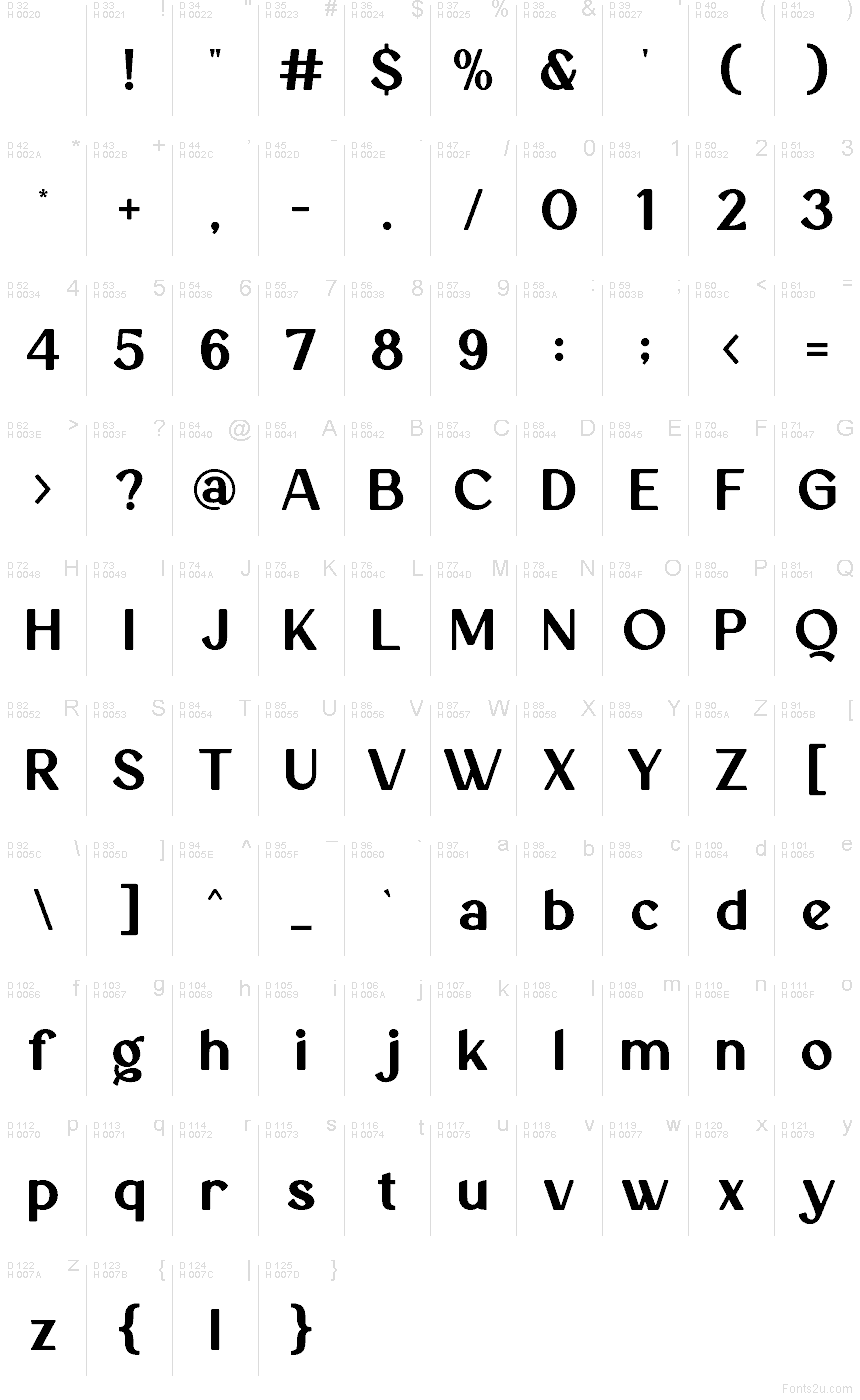
Qarume Regular
A fonte Qarume, da ErmediaStudio, é uma tipografia sem serifa gratuita que transforma geometria simples em algo caloroso e carismático. Seus vazados largos e arredondados, curvas robustas e cortes angulares inesperados conferem a cada letra um charme amigável e artesanal, mantendo um visual limpo e moderno. Os traços possuem um aspecto quase de tinta ou pincel nas bordas, dando ao texto um ritmo suave e humano, em vez de uma linha fria e mecânica.
Com a Qarume, você obtém uma fonte sem serifa que é ao mesmo tempo acessível e marcante para branding, embalagens, cartazes, gráficos para redes sociais, logotipos e títulos expressivos. As formas generosas funcionam lindamente em tamanhos maiores, onde os cortes e curvas sutis realmente se destacam. Combine esta fonte gratuita com uma grotesk leve e neutra para o texto principal e deixe a Qarume brilhar nos momentos mais autênticos e arrojados do seu layout.